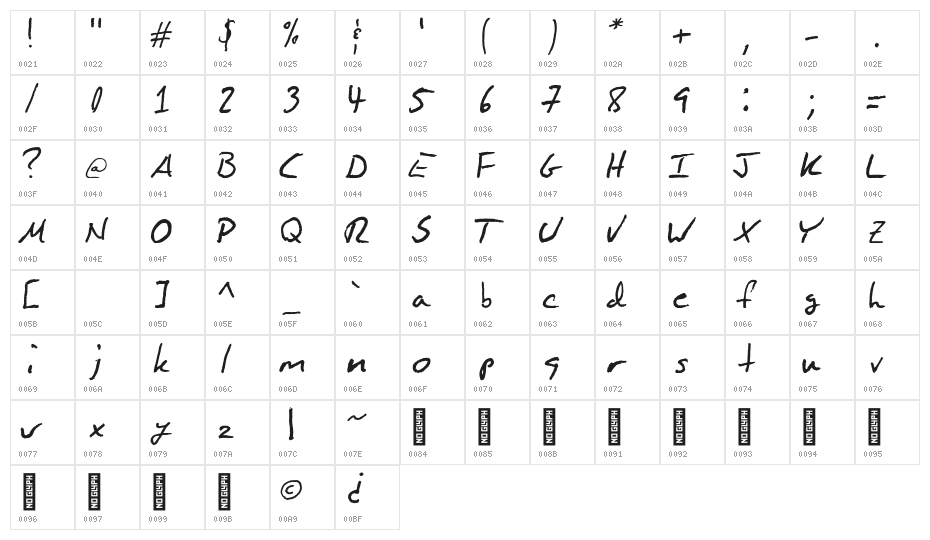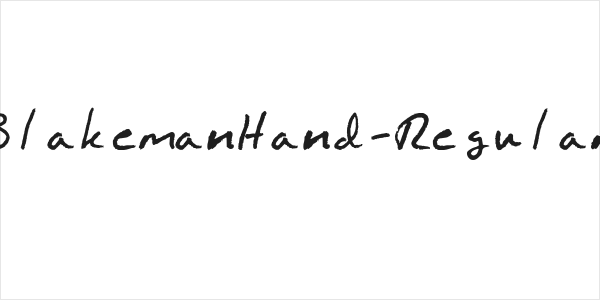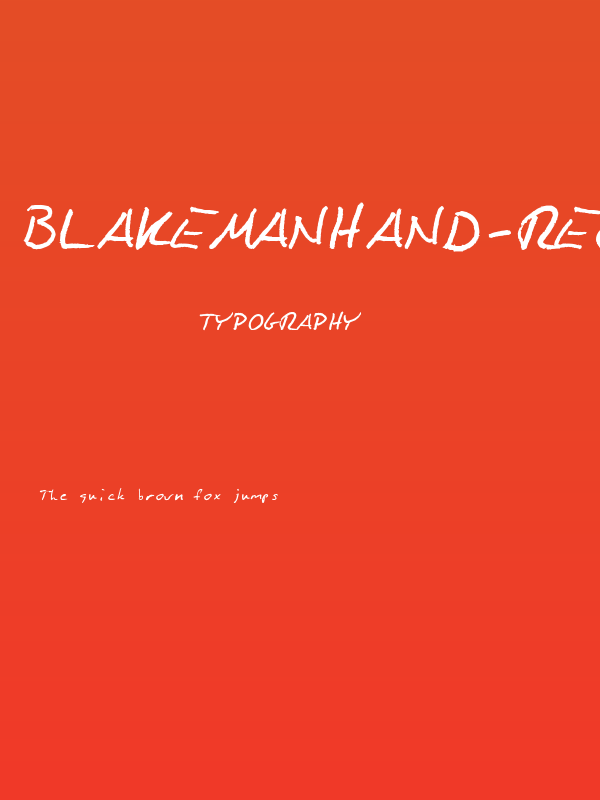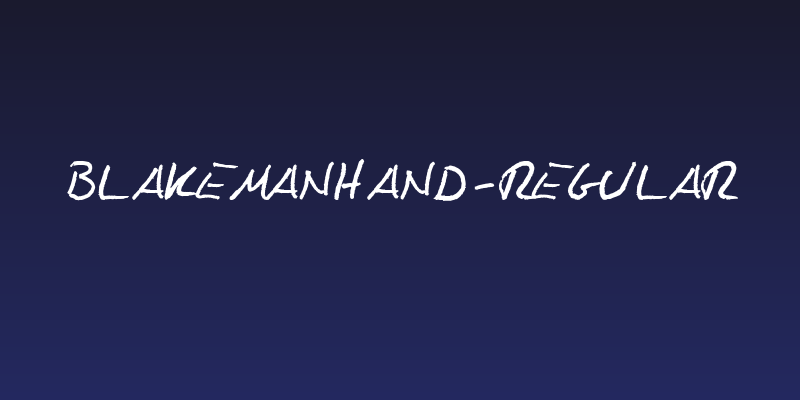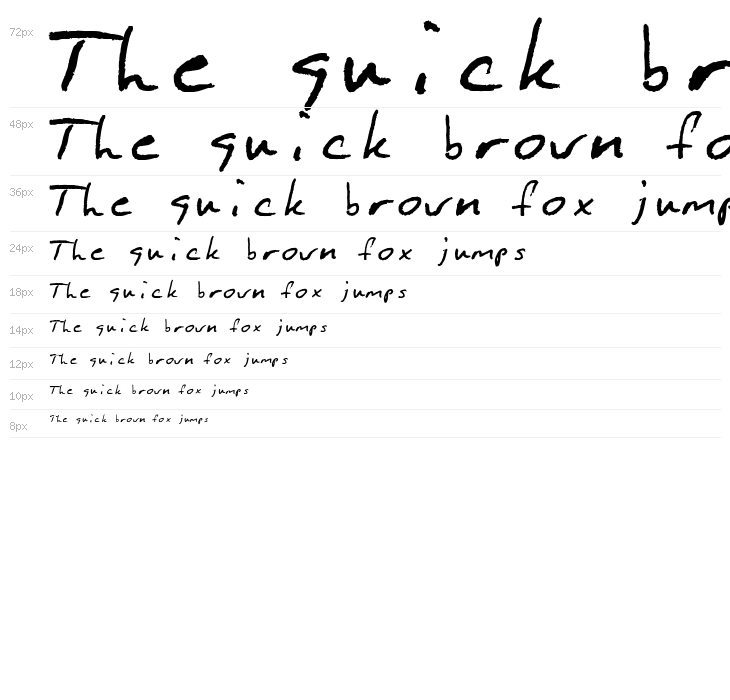
BlakemanHand-Regular Font
| Estilo general | Casual, Artistic |
| Caso de uso | Logos, Invitations, Greeting Cards |
| Proyectos propuestos | Ideal for personal notes, invitations, greeting cards, and artistic projects that benefit from a handwritten touch. |